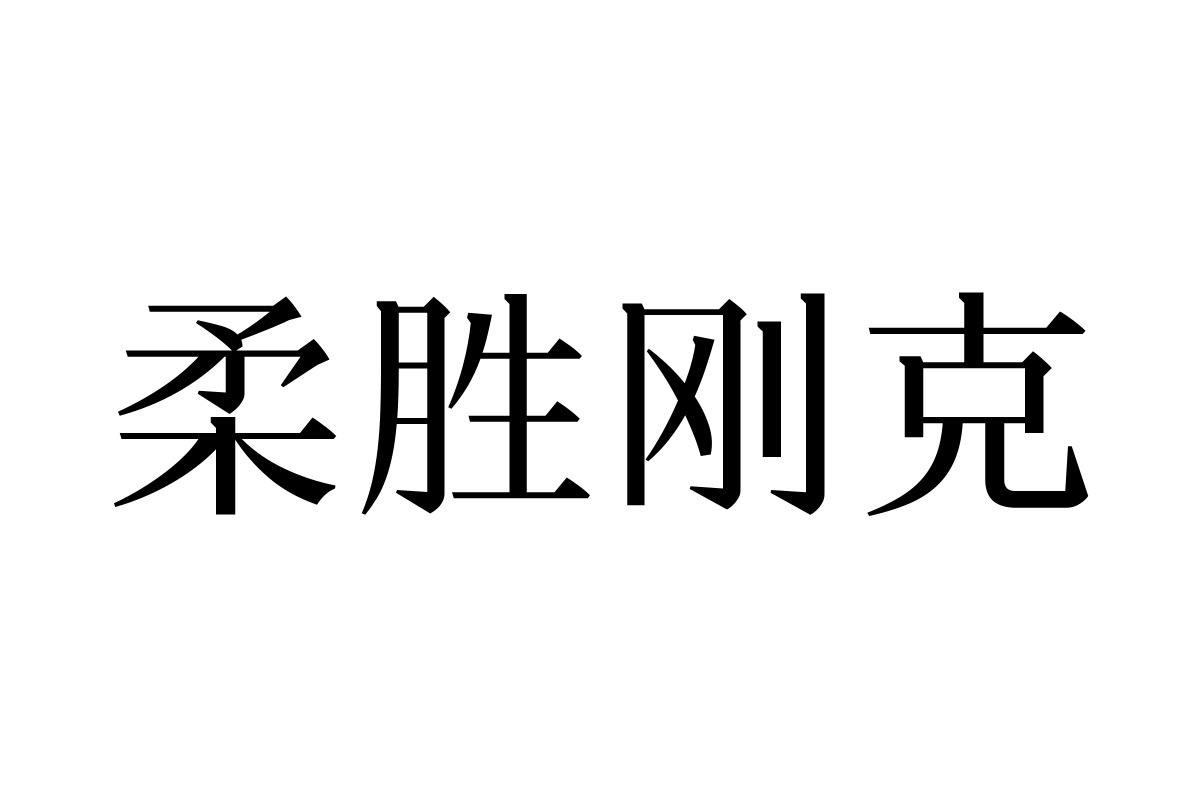
汉仪新人文宋 55W是一款现代简约风格的中文字体,由汉仪字库设计。这款字体具有优雅流畅的线条和清晰的字形结构,给人一种简洁明快的感觉。它的笔画粗细适中,既适合标题文字,也适合正文文字。在设计上,汉仪新人文宋 55W注重细节处理,使得整体效果更加和谐统一。这款字体适用于各种需要简洁、明快设计风格的场合,如广告、海报、杂志等。